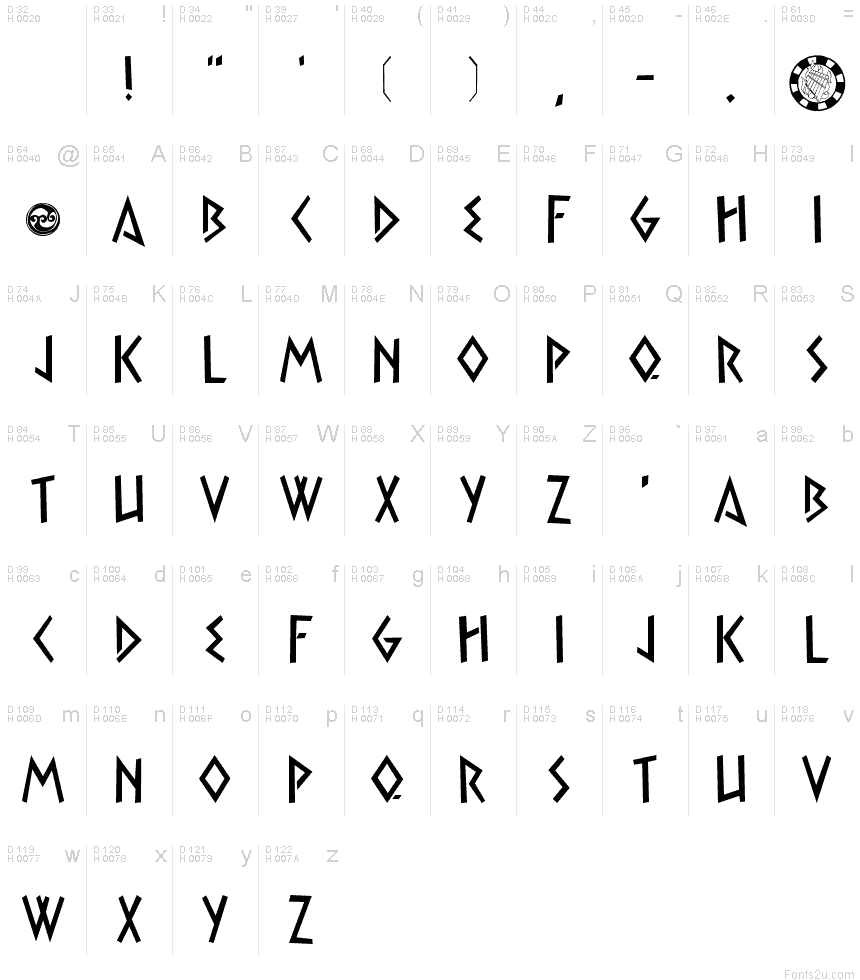
Satyr Passionate autorstwa Briana Powersa to darmowy krój displayowy (wielkie litery), inspirowany estetyką grecką, o surowym, mitycznym charakterze. Litery opierają się na ostrych kątach, nierównych pociągnięciach i rozłupanych, przypominających włócznie formach. Całość balansuje między antycznymi napisami a liternictwem w stylu fantasy, nadając krojowi niespokojną, rzeźbioną ręcznie energię.
Krój ten naturalnie pasuje do logotypów gier, otwarć rozdziałów, nagłówków plakatów, okładek albumów i plansz tytułowych, gdzie pożądany jest szorstki, klasyczny klimat. Jako darmowy font, świetnie sprawdzi się również w monogramach i krótkich napisach, ponieważ te postrzępione sylwetki liter robią wrażenie, zanim jeszcze zdążymy przeczytać słowo.
A free font made by Brian Powers, from Changeling: The Dreaming.